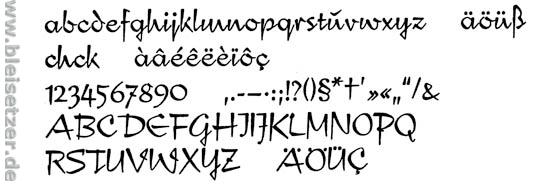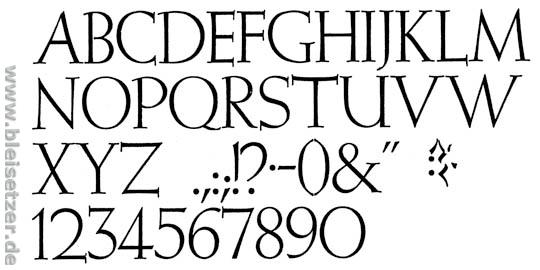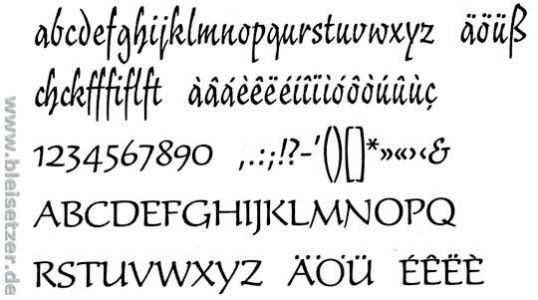
Ausgewogene Pinselschrift gesucht
Für das Cover eines Buches "Chinesische Kalligraphie" suche ich eine Pinselschrift. Das ist zwar platt, aber der Verlag findet's trotzdem originell. "Wenigstens nicht 'Mandarin'", dachte ich da.
Ich selbst habe aber leider nun ein viel zu differenziertes Bild vom Duktus chinesischer Kalligraphie (ich muss gestehen, ich liefere auch den Inhalt des Buches), als dass mich sowas wie "Mirage" befriedigen würde.
Nun ist mir aber alles, was ich sonst so finde, zu unausgewogen, und die einzige Pinselschrift, die ich kenne und die dem chinesischen Pinselstrich ernsthaft nahekommt ("Azuki" von J. Latham) ist in diesem Fall zu "bold".
Eigentlich sollte mein Wunschfont stehen wie eine Antiqua, aber die Brüchigkeit eines Pinselstrichs haben.
Irgendwelche Vorschläge? Und bitte keine langen Listen, denn Unentschlossenheit ist ja gerade mein Problem.
wie gefällt Dir denn die Typo-Skript (Daphne)?
Die gibt es auch als digitalen Font.
Der Kollege Mojuba schreibt hier in diesem Forum in einer Diskussion über diese Schrift:
"Die Typoskrpt (Daphne) ist völlig aus der Kalligraphie heraus entstanden, was nicht verwundert, denn Hildegard Korger ist in erster Linie eine begnadete Kalligraphin. Ich bin nach wie vor der Meinung, daß nach einem ersten 'Ooops, die sehen aber ähnlich aus...' die Läuterung kommen sollte, denn diese beiden Fonts sind bei weitem unähnlicher, als es z.B. Helvetica und Akzidenz-Grotesk sein könnten."
Die Schrift gibt halt Antwort auf Deine Anforderungen:
Chinesisch, Kalligraphie und Antiqua. Das gäbe Dir Möglichkeiten zum Spielen. Eine Versalzeile würde einen interessanten Gegensatz zu einer gemischten Unterzeile geben.
Würde aber sicher auch gehen, daß Georg dir die gewünschten Zeilen absetzt und du sie irgendwie einscannst und so einbauen kannst. Oder?
Ach, Du bist das, der der Kollege aus der Daphne-Diskussion.. :)
Grundsätzlich kann ich bei konkretem Bedarf und so wie jetzt, wenn es anders vielleicht zu aufwendig ist, gern Zeilen im Bleisatz absetzen und einem Kollegen hier Andrucke zur Verfügung stellen.
Die Daphne habe ich noch in 20 p.
die Daphne war ein Volltreffer - leider nur insofern, als dass der Vorgängertitel desselben Verlages (mit dem das neue Buch nicht verwechselt werden soll) die Daphne fürs Cover verwendet, wie ich heute morgen feststellen musste. Schade.
Die Suche geht also weiter ...
Noch ein Vorschlag:
Was hältst Du denn von der Compliment:
Ich kann mir nicht vorstellen, daß es die nicht auch als Font gibt; auch, wenn ich sie auf Anhieb nicht finde. Aber da kennst Du Dich eh besser aus.
Ein, hmmja, Freund von mir, der sich mit seiner chinesischen Freundin auf eine Reise in ihr Heimatland machte hat eine Photoseite mit der Skin Deep von Blambot übertitelt. Sehr schön, wie ich finde. Weiß ja nicht ob's deinem Projekt hilfreich ist, wollte aber nunmal auf diese Schönheit hinweisen.
Achja, nochwas: hast du schon Alejandro Pauls "Bluemlein Scripts" durchforstet, schon seine Affair gesehen? Und die neue Sinfonieta hat auch was.
Was hältst Du denn von der Compliment? Ich kann mir nicht vorstellen, daß es die nicht auch als Font gibt; auch, wenn ich sie auf Anhieb nicht finde.
Richtig, Georg. Aber kein Wunder, dass du sie nicht findest, die ist auch reichlich versteckt. Der Großteil der Schrift wurde von Rick Mueller unter dem Namen New Day Script digitalisiert. Was Rick Mueller dazu noch zu sagen hat steht hier, zum Beispiel dass sie auch als "Birthday" bekannt sein soll. Obs davon eine kommerzielle Variante gibt, weiß ich nicht …
Dieser Herr Mueller hat also diese Schriften digitalisiert.
War das legal? Oder hat er's halt gemacht und schert sich nicht um Lizenzen?
Und warum bietet er sie jetzt kostenlos an? Bzw.: macht er das?
Nur aus Freude an der Sache?
Das müßten dann doch eigentlich die Schrift-Entwerfer, die ihren Lebensunterhalt damit betreiben, nicht so gern sehen, oder?
Meine Näherung:
Ich denke, dass einige Leute, wie auch der oft zitierte Dieter Steffmann, es sich zur Aufgabe gemacht haben, Schriften, die "analog" entworfen wurden, ins digitale Zeitalter hinüber zu retten. Was an sich eine lobenswerte Idee ist, da man ja weiß dass vieles was nicht digital vorhanden ist, allzuschnell in Vergessenheit gerät.
So empfände ich auch ein Buch über China.
Dieses ruhige Selbstbewußtsein und, aus meiner Sicht, das fremde und ungewöhnliche.
Sehr schön. Wenn das von deiner Hand stammt: sei so verwegen und male die Schrift selbst. Wahrscheinlich werden im Wort die einzelnen Buchstaben etwas weniger Detailreich sein dürfen als dieses C, aber diese Hand kann das.